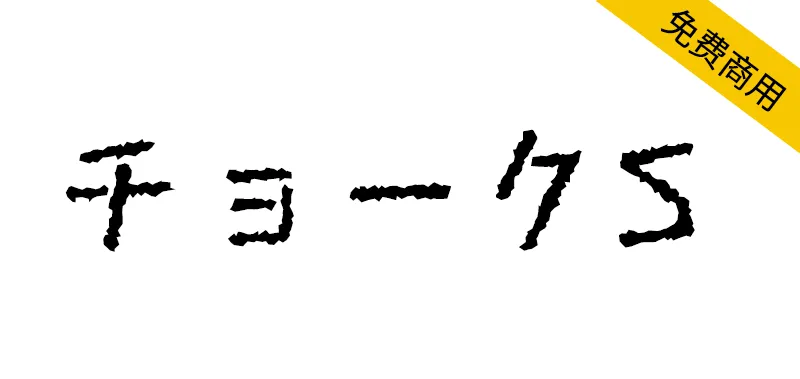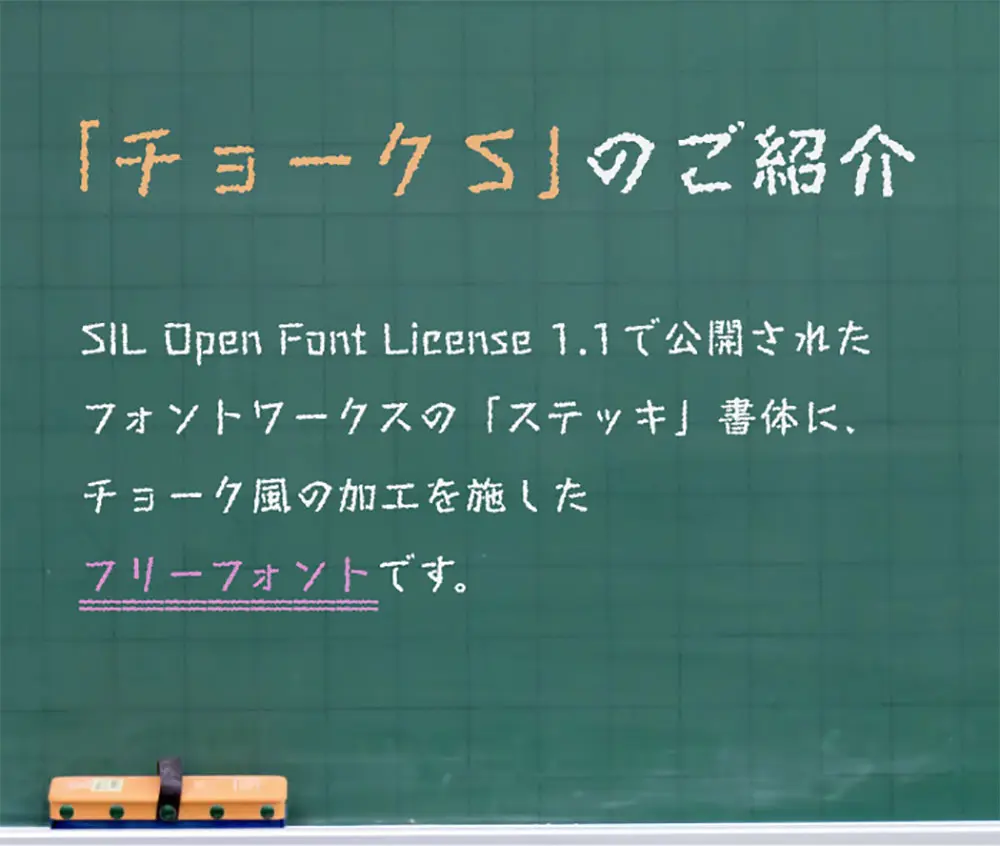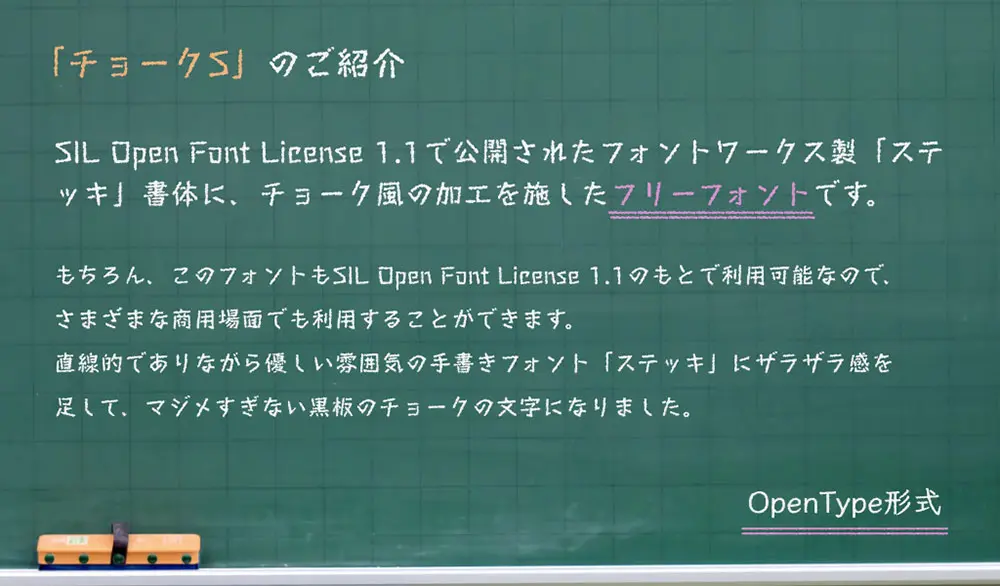
粉筆體S(チョークS)是一種看起來像是用粉筆寫在黑板上的字體,和另外一款 粉筆體(チョーク體)相比,粉筆體S的設計更粗,破損感、手寫感更強烈些。
此字體是Fontworks製造的字體「Stick(ステッキ)」的修改版本,該字體採用SIL Open Font License 1.1中發佈。通過加粗設計,該設計具有更強的粉筆般的感覺。
「チョーク體」とは別に、さらに砕けた雰囲気のチョークっぽいデザインのフォント「チョークS」を公開しました。
このフォントは、先日「SIL Open Font License 1.1」で公開されたフォントワークス社製の書體「Stick(ステッキ)」を改変したフォントです。ラフ処理を加えることで、ザラザラ感のあるデザインになり、チョーク風の雰囲気に仕上がりました。